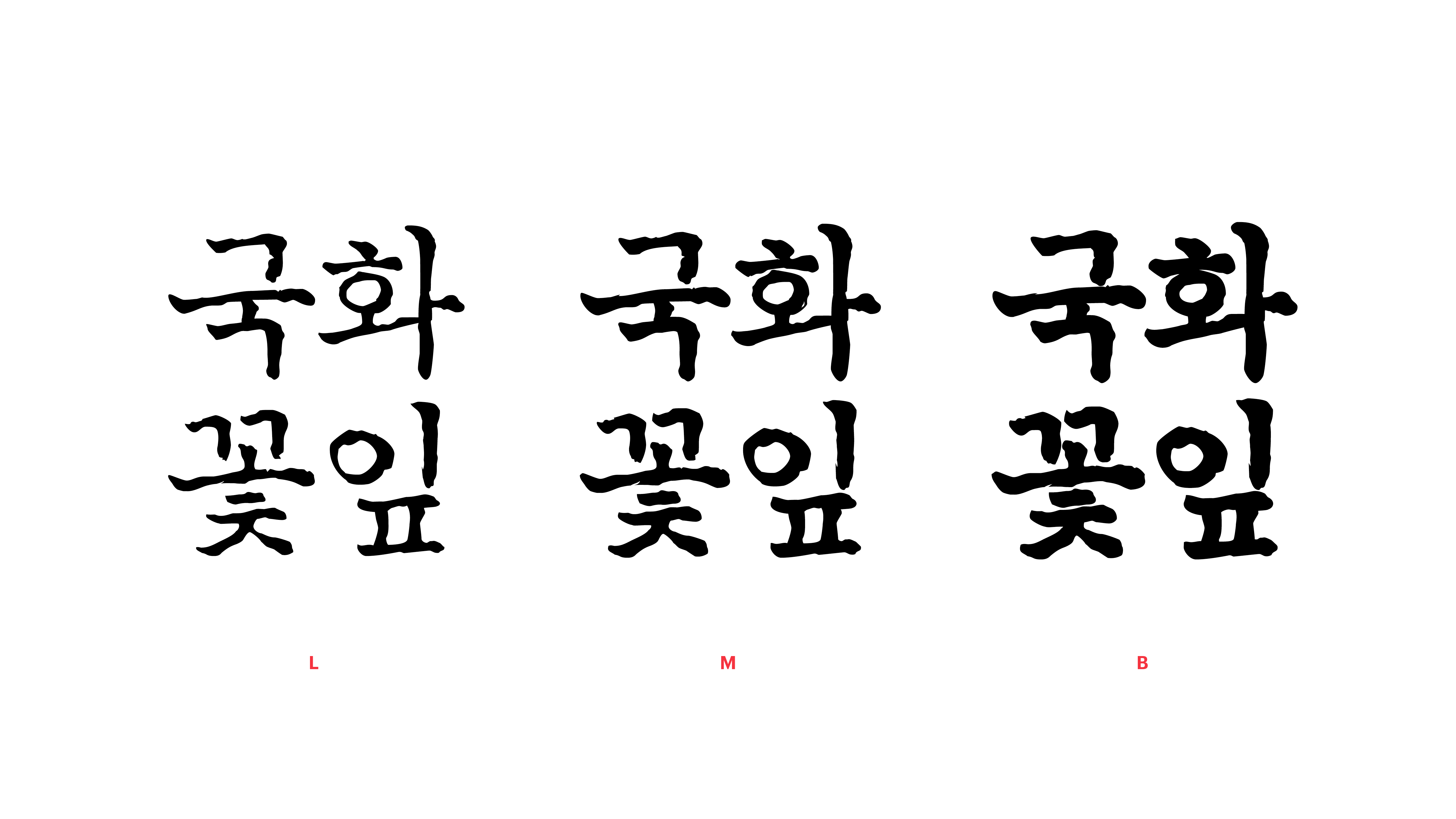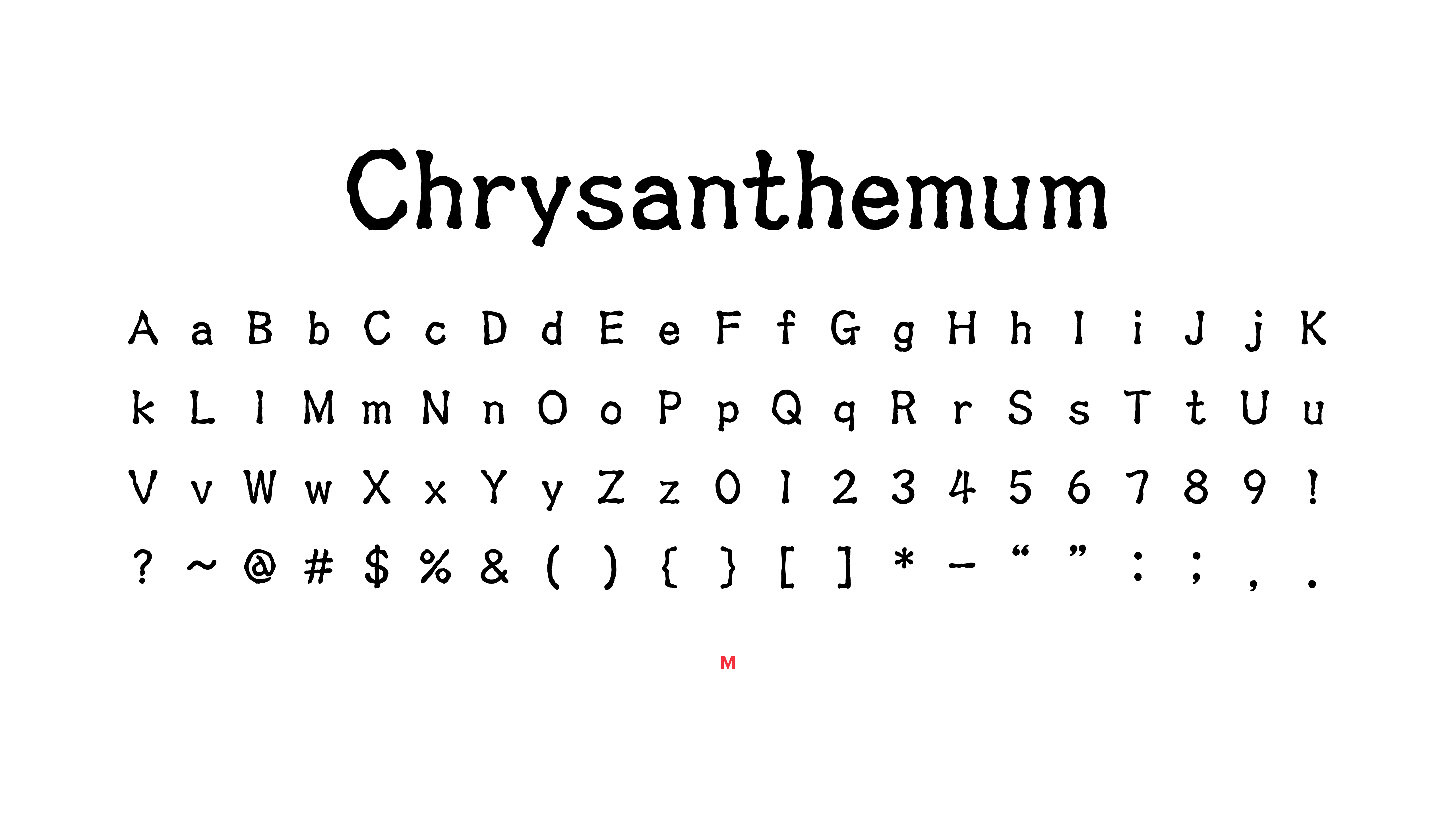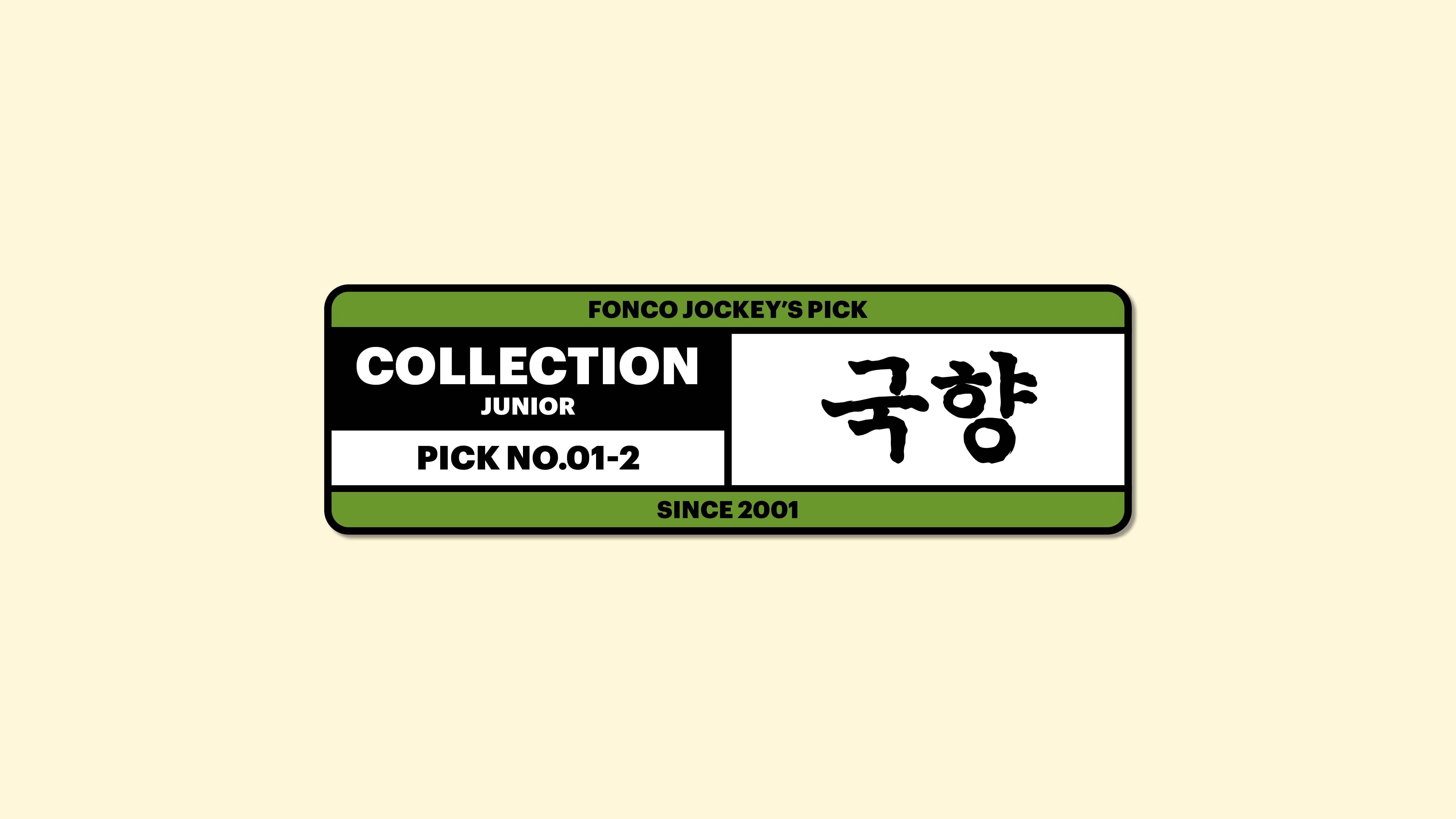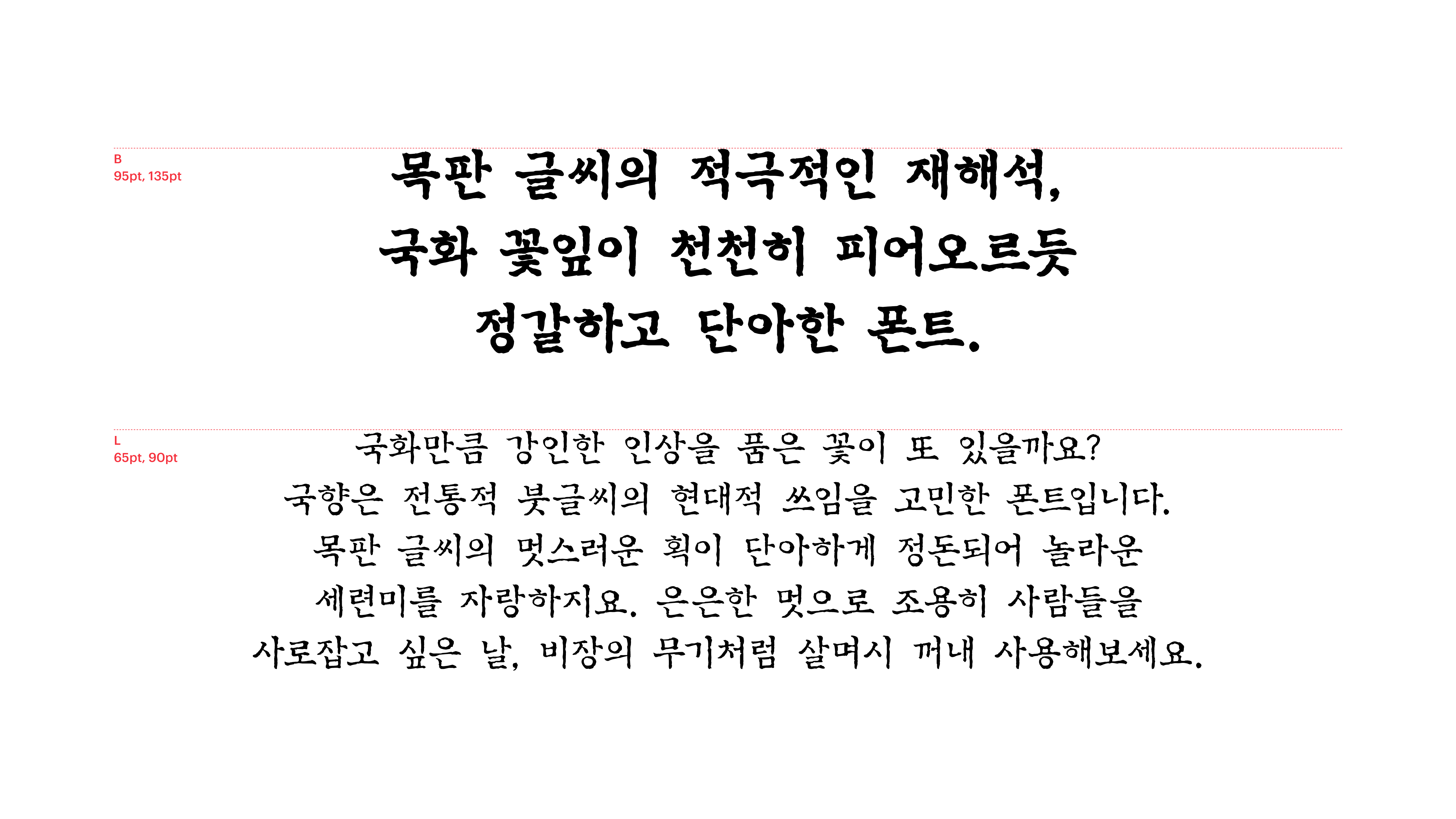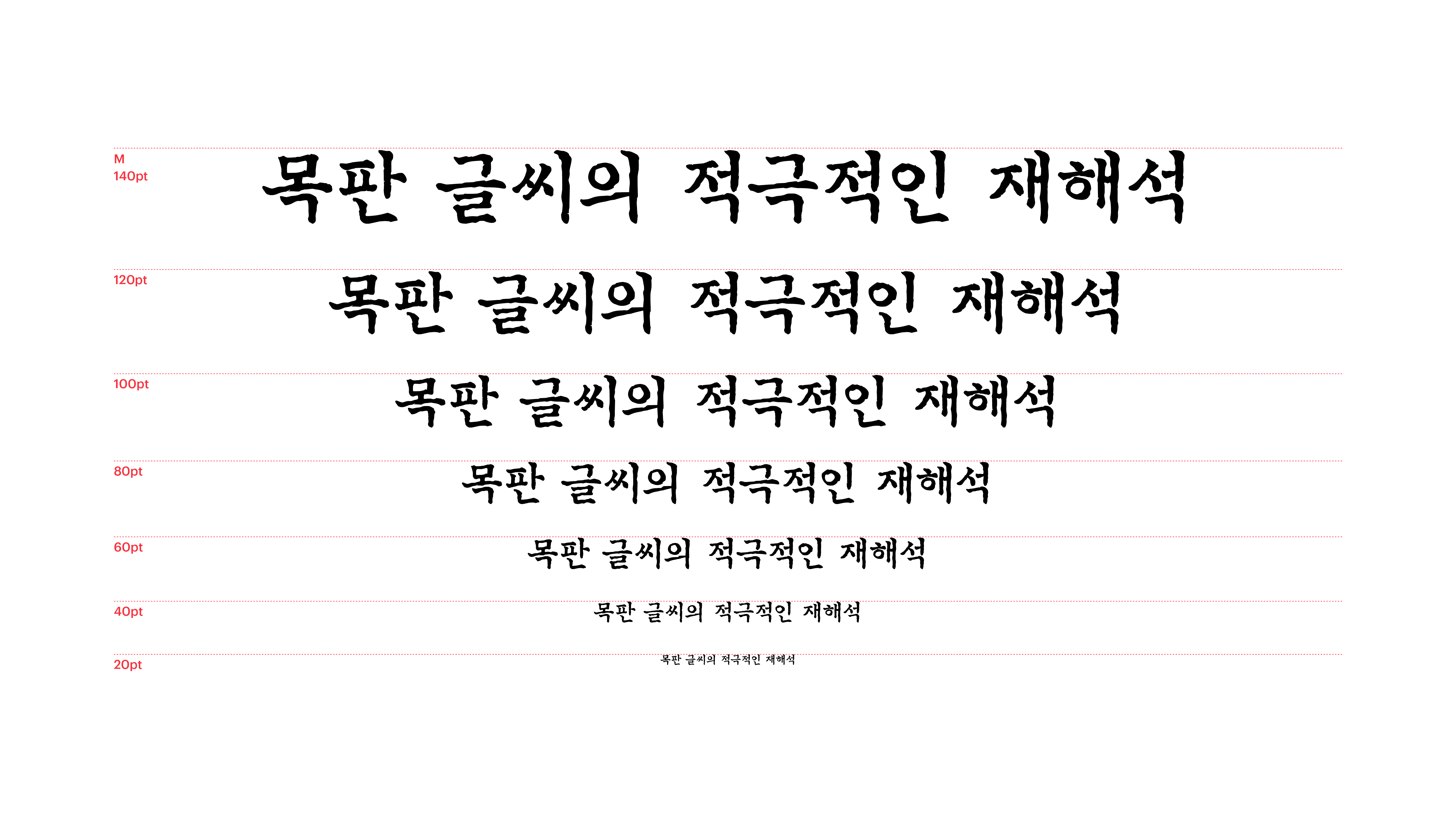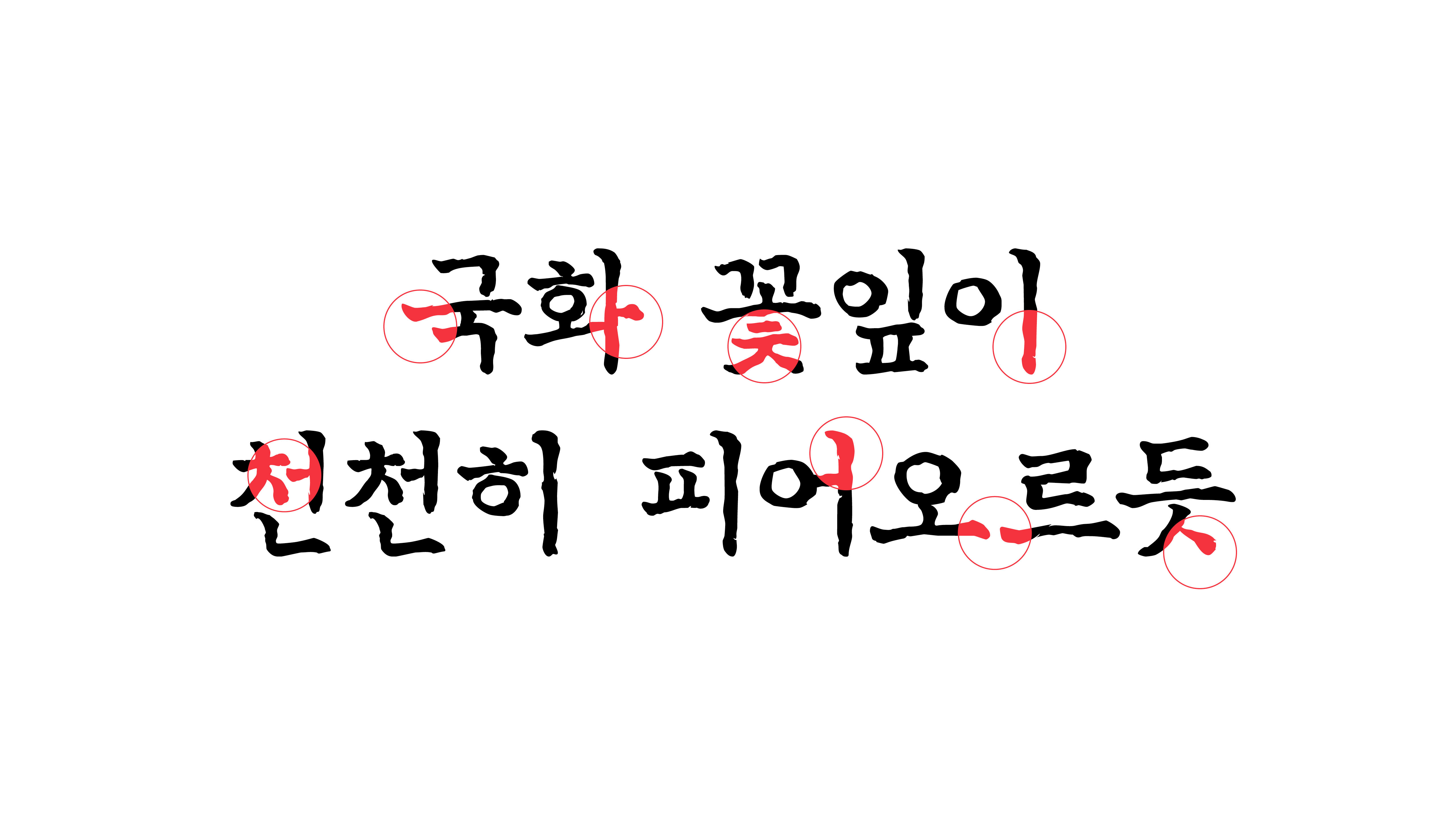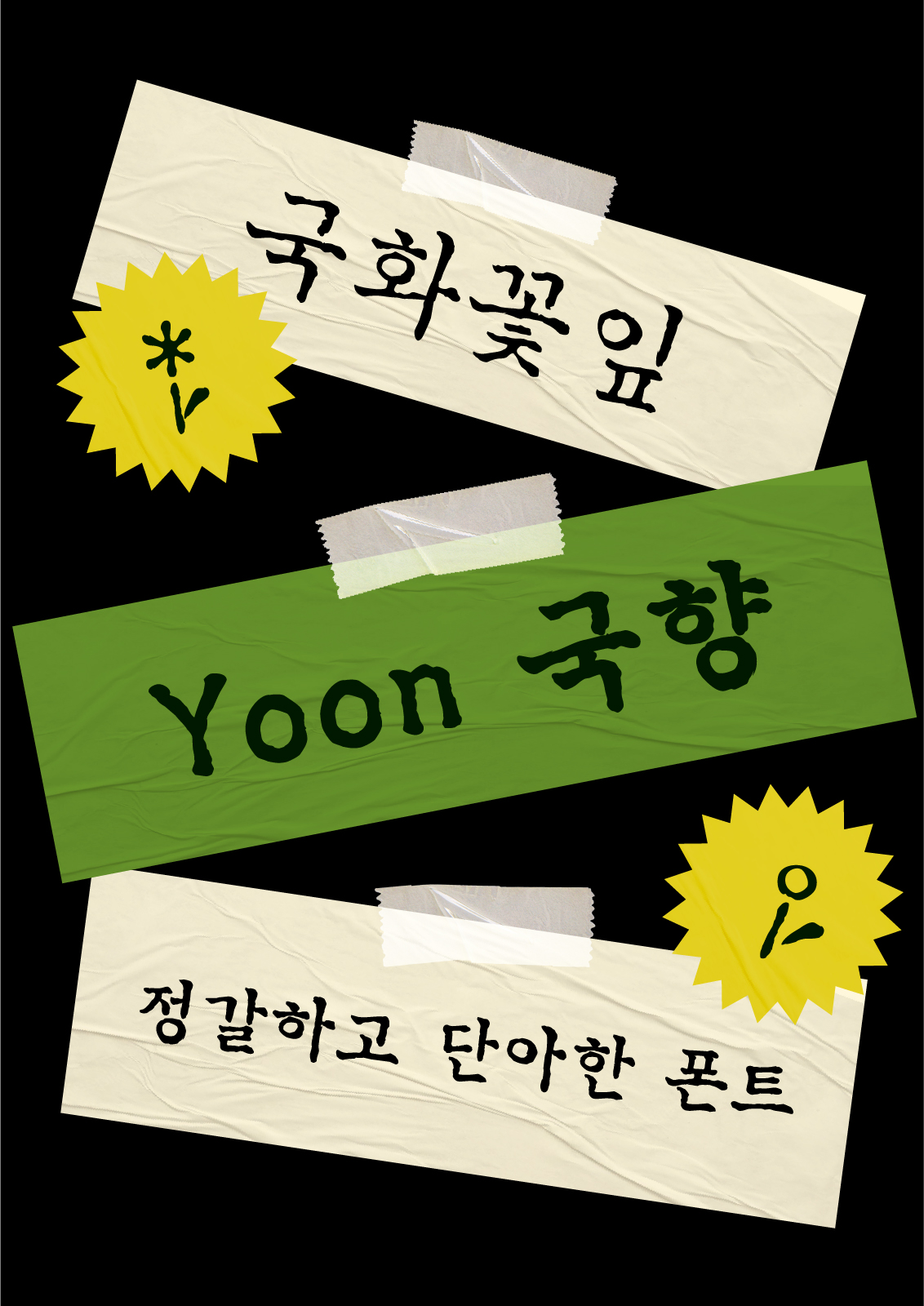
국향
Yoon 국향
국화만큼 강인한 인상을 품은 꽃이 또 있을까요? 국향은 전통적 붓글씨의 현대적 쓰임을 고민한 폰트입니다. 목판 글씨의 멋스러운 획이 단아하게 정돈되어 놀라운 세련미를 자랑하지요. 은은한 멋으로 조용히 사람들을 사로잡고 싶은 날, 비장의 무기처럼 살며시 꺼내 사용해보세요.